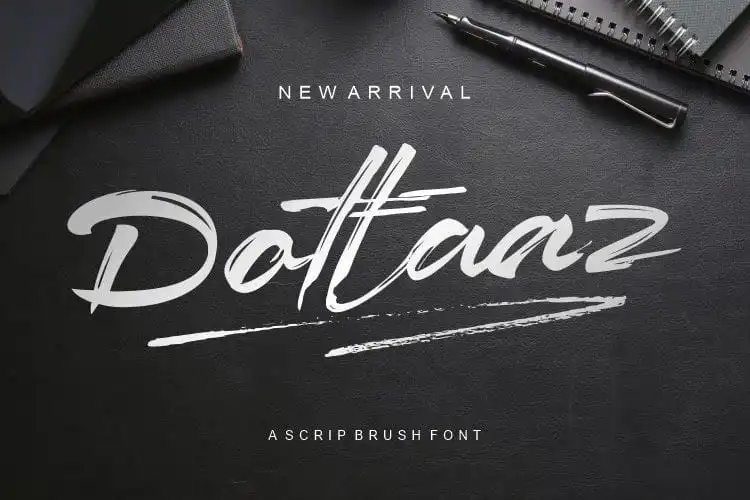
Dottaz Brush Font – Download Grátis
A Dottaz Brush Font é uma opção moderna para quem procura um estilo que combine escrita à mão com borracha. Artype07 criou essa fonte exclusiva, disponível no artypedesigns, e compartilhou-a com o mundo. Seu principal charme reside em sua versão à mão livre combinada com a elegância da borracha, resultando em projetos de design modernos e atraentes. É ideal para qualquer projeto profissional que busque uma identidade forte. Para ideias criativas como casamentos, marcações ou logo, ou mesmo frases inspiradoras, a Mightwell é uma escolha perfeita. A Dottaz Brush Font oferece um toque personalizado e único aos seus projetos, tornando-os ainda mais únicos e cativantes.